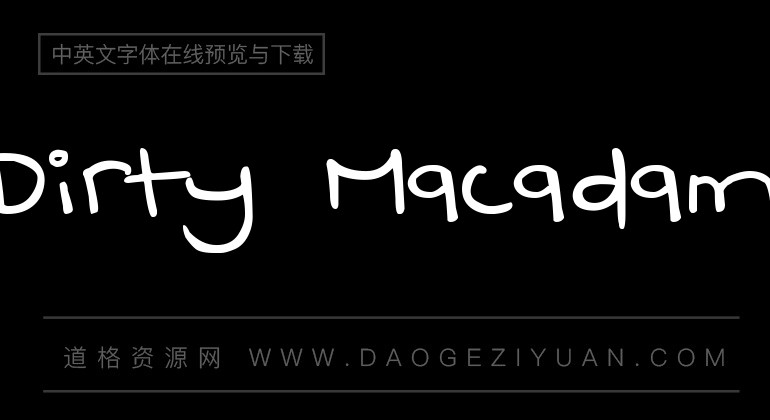
Dirty Macadam
? Dirty Macadam 是一款粗犷而有趣的手写字体,它的设计灵感来自于把破旧的沥青路面比作一本书,它的每一个字母都有自己的故事,而这些故事就像沥青路面上的痕迹一样,它们构成了一个独特的字体。Dirty Macadam 字体拥有极具质感的外观,它可以用于各种印刷品的设计,例如海报,书籍,杂志,T恤等等。
Dirty Macadam是一款非常不错的手写艺术字体,具有很好的视觉感,适合于文化类的宣传设计、商业类品牌的广告和产品包装设计以及个性化文字排版等较多场景。